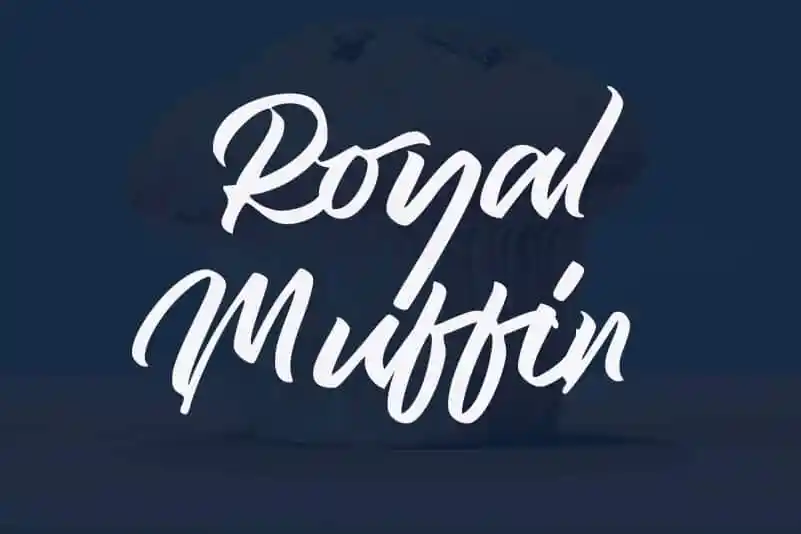
Royal Muffin Script Font – Download Grátis
Descubra a Royal Muffin Script Font, uma elegante tipografia script desenvolvida por M.0Type. Inspirada nas marcas artesanais utilizadas para criação de placas de lojas, rótulos de marca e anúncios promocionais ao ar livre, essa fonte foi concebida para capturar o aspecto natural da pintura a mangueira. Royal Muffin é perfeito para quem deseja adicionar uma atmosfera única e autêntica aos seus projetos digitais. Com sua aparência fluida e vibrante, essa fonte oferece uma maneira fácil de criar logotipos e tipografia para artes gráficas em estilos variados com um simples toque de seu teclado. Essencialmente feita para designers criativos que buscam incorporar um pouco do mundo real no design digital. Não perca a oportunidade de transformar seus projetos digitais em algo mais autêntico e vibrante com Royal Muffin Script Font.